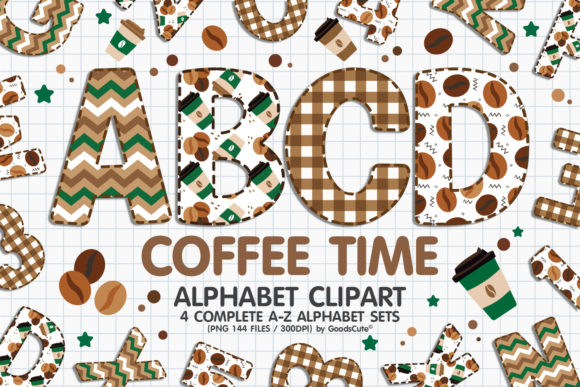
Coffee Time Alphabet Letters Sublimation
Mencari elemen reka bentuk yang sesuai boleh menjadi mencabar, tetapi Coffee Time Alphabet Letters Sublimation menawarkan koleksi luar biasa yang menaik taraf karya anda serta-merta.